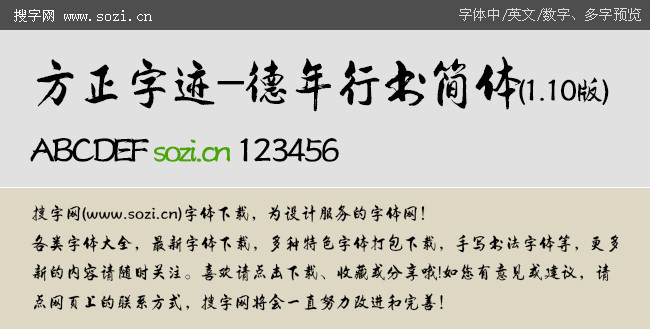
方正字跡-德年行書簡(jiǎn)體
搜字網(wǎng)提供一款方正字跡-德年行書簡(jiǎn)體中文字體下載,方正字跡-德年行書簡(jiǎn)體是方正字庫創(chuàng)作的一款創(chuàng)意字體,該字體書寫功力圓熟,用筆剛健爽快,筆力遒勁,筆畫渾厚寬闊,洋溢著當(dāng)代書寫美感,能夠適用于藝術(shù)設(shè)計(jì)、包裝印刷、簽名設(shè)計(jì)等應(yīng)用。(本字體為個(gè)人非商用版,如需要商用請(qǐng)聯(lián)系方正公司購買版權(quán))